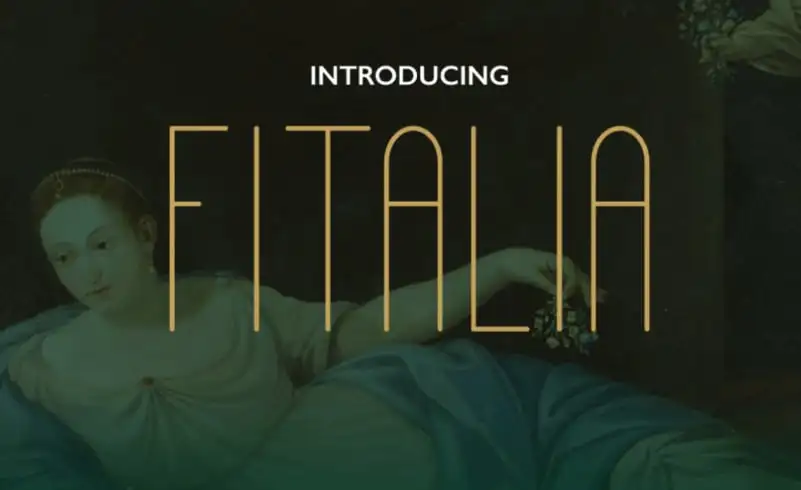
Fitalia Sans Serif Font – Download Grátis
Introduzimos a Fitalia Sans Serif Font! Se você está à procura de uma fonte sans-serif em caixa alta que combine romantismo com simplicidade e minimalismo, encontrará exatamente isso na Fitalia. Desenhada pelo designer Hamilton, esta fonte é perfeita para ambientes digitais variados. Com um aspecto elegante devido à sua forma simples, o espaçamento fino e as bordas suaves, a Fitalia se destaca por suas formas geométricas limpas e modernas. Este estilo da fonte foi projetado inicialmente para utilização em cabeçalhos ou subtítulos e é ideal para visualizar muitos tipos de projetos visuais. A Fitalia tem um aspecto minimalista mas elegante, adequando-se perfeitamente a uma variedade de ambientes digitais. É perfeita para criar um impacto forte em sua próxima criação gráfica ou projeto editorial. Não hesite em experimentar a Fitalia e veja por si mesmo como ela se destaca na web moderna.